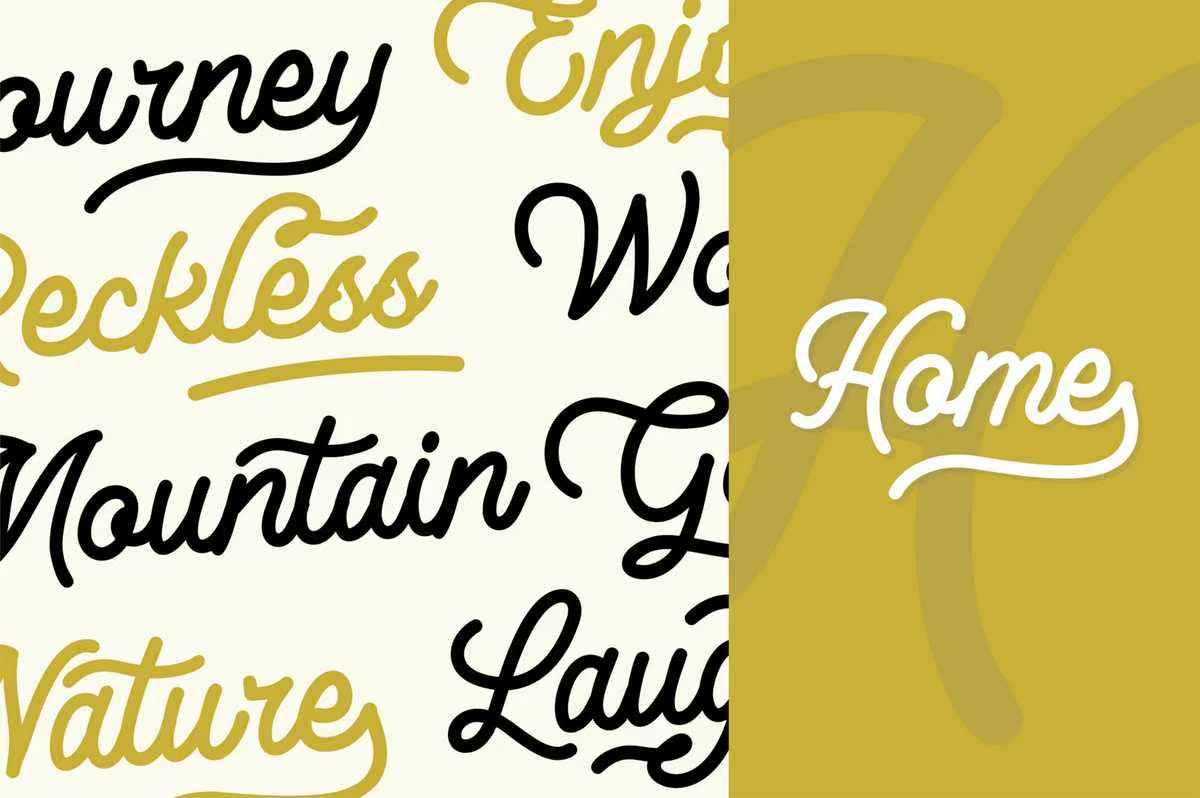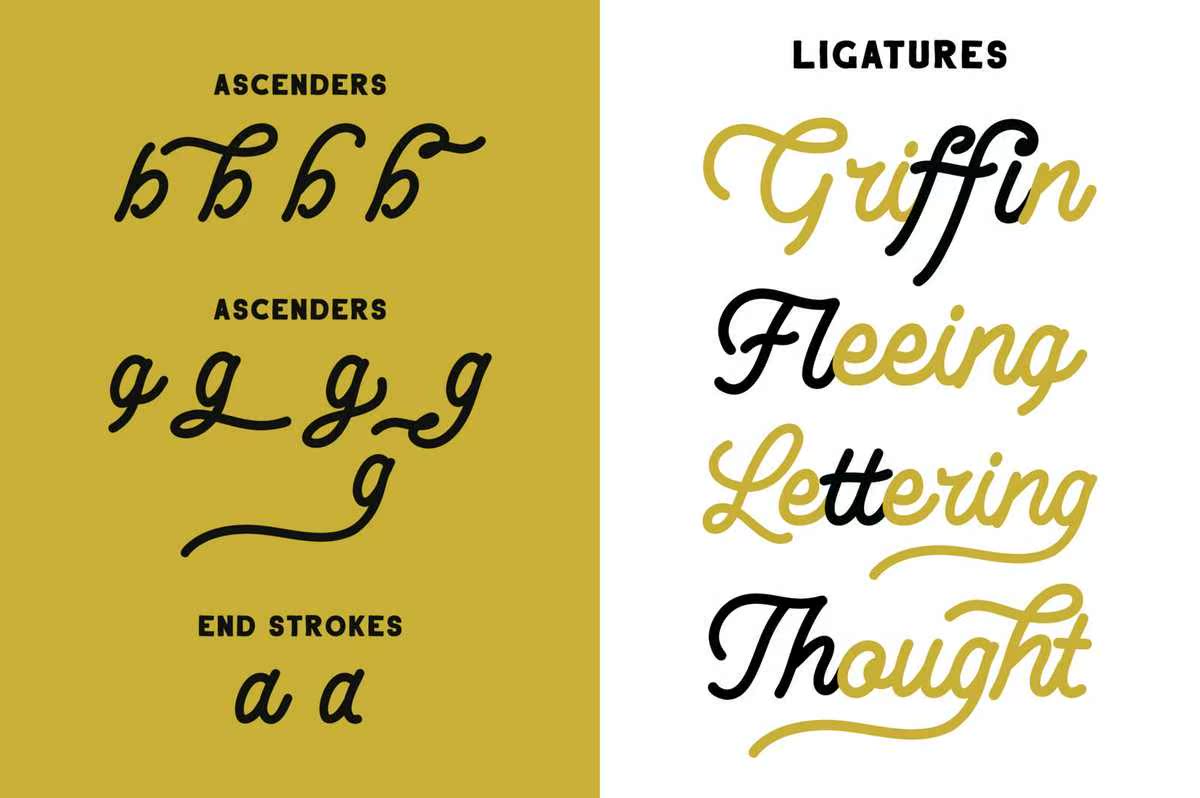
Lesley是一款高质量的Monoline Scription Font,具有由AdventorousVibea和VintageDesign设计的水洗功能。多种字体功能,具有风格替换、擦洗、连字、风格设置、终端格式和装饰,可让您的设计充满青春气息并搭配成对的文字。此Font适用于VintageDesign、t恤、徽标、标签、徽章、,postersandetc.Lesley是一款高品质的Monoline脚本字体,带有由AdventorousVibea和VintageDesign设计的水洗图案。多个字体功能,具有风格替换、擦洗、连字、风格设置、终端格式和标记,可让您的设计更具吸引力,并可搭配成对的文字。此字体适用于葡萄酒设计、t恤、徽标、标签、徽章和postersandetc。